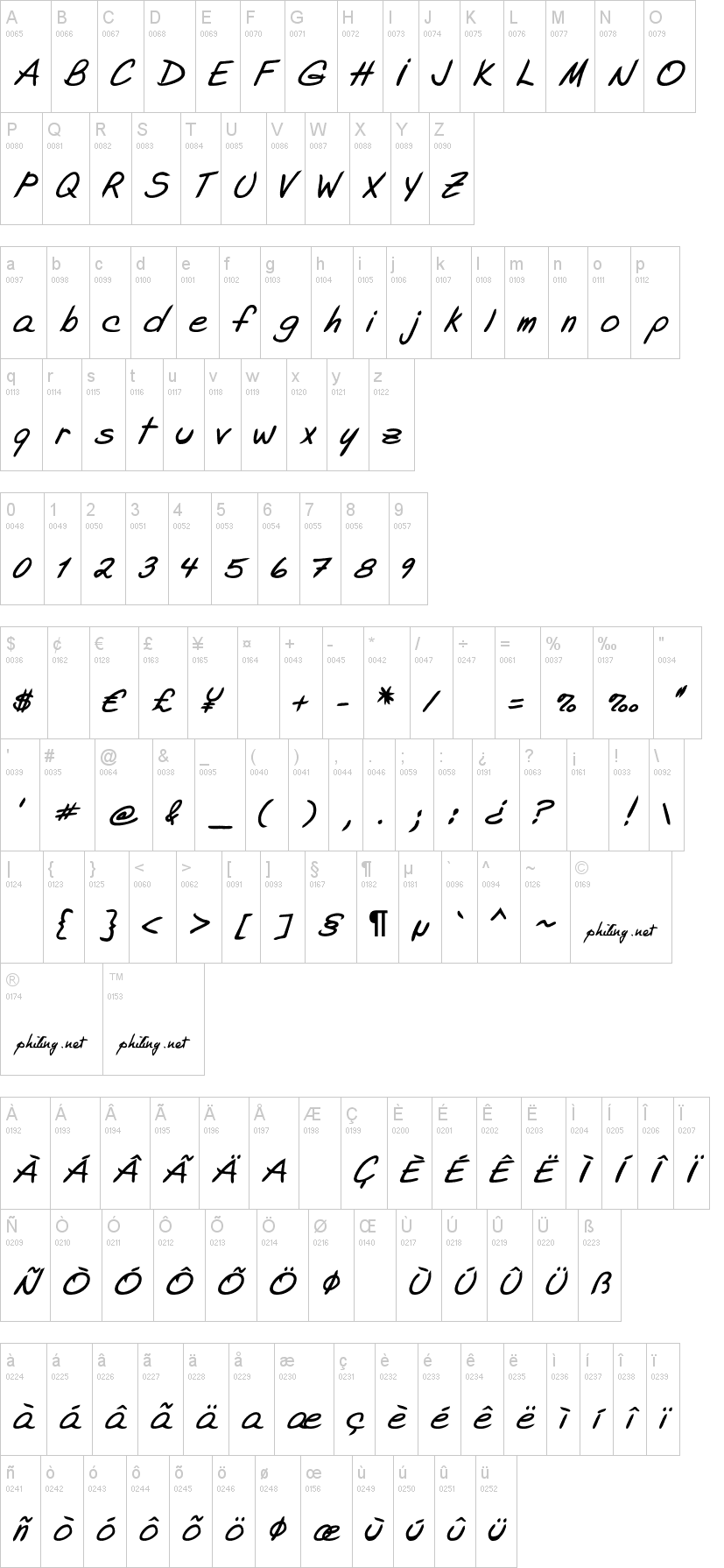
Adelyne
Adelyne是一种优美而精致的手写风格字体,具有独特的笔画和精美的装饰元素。它是由Laura Worthington设计的,适用于各种设计项目,如印刷品、包装设计、网站设计、品牌标识等。 Adelyne字体家族包括Adelyne Regular、Adelyne Bold、Adelyne Script等多种变体,每种变体都具有不同的特点和用途。Adelyne Regular字体是一种有机的手写风格,适合用于印刷品和数字设计。Adelyne Bold字体则更加粗壮有力,适合用于海报和标题设计。Adelyne Script字体具有流畅的笔画和装饰元素,适合用于品牌标识和广告设计。 总之,Adelyne字体是一种优美、精致而多样化的字体,适用于各种设计项目,可以增强设计的美感和艺术性。
Adelyne是一款非常不错的手写艺术字体,具有很好的视觉感,适合于文化类的宣传设计、商业类品牌的广告和产品包装设计以及个性化文字排版等较多场景。
Adelyne字符映射图